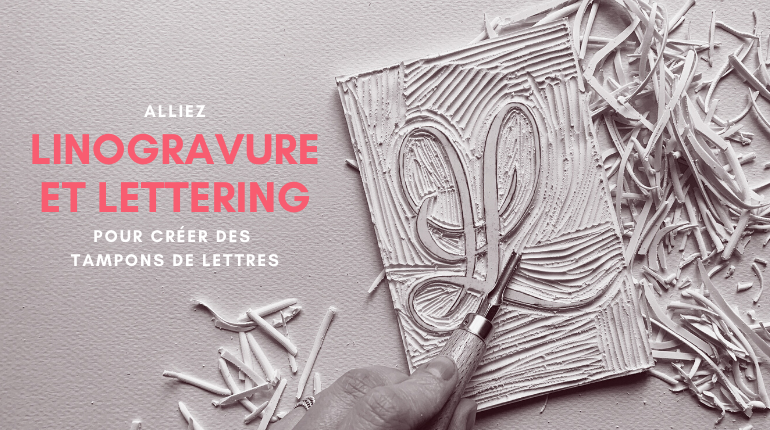
Alliez linogravure et lettering pour créer vos propres tampons de lettres
Cet article est pour tous ceux qui veulent changer de supports, d’outils et de matériaux. Fini le feutre pinceaux et la plume, place à la linogravure !
Vous connaissez ? C’est une technique de gravure qui consiste à évider certaines parties de la gomme à graver et à encrer les parties intactes (non évidées), pour imprimer le motif qu’on a ainsi créé.
C’est une super méthode pour créer des tampons de motifs et des tampons de lettres (appel à tous les fans de bullet journal !).
Pour cet exemple, j’ai allié la linogravure avec le lettering en dessinant le logo de mon studio Letter Your Life. C’est un super moyen pour dessiner des lettres et les tamponner à l’infini !
Le matériel de linogravure
Pour ce tutoriel, vous aurez besoin du matériel suivant:
- Un crayon à papier
- De la gomme à graver (ici j’ai acheté la gomme extra tendre 4mm 15x10cm de chez Essdee)
- Une gouge avec plusieurs embouts interchangeables
- Une peinture spéciale linogravure ou une peinture acrylique de la couleur que vous voulez
- Un rouleau à peindre en mousse ou un rouleau à encrer si vous avez plus de budget
Vous avez plusieurs options pour le motif :
- Partir d’un motif déjà existant en utilisant un iPad et du papier calque (ou un motif imprimé et du papier calque)
- Inventer un motif directement sur la gomme à graver
Si vous choisissez cette option, vous pouvez passer directement à l’étape 2
Etape par étape
- Appliquez une feuille de papier calque au dessus du motif que vous souhaitez faire en linogravure et tracez les contours du motif au crayon à papier.
- Retournez la feuille de papier calque à l’envers et placez la au dessus de la gomme à graver. Attention, votre motif ne doit pas dépasser la surface de la gomme.
Une fois que votre motif est bien centré, repassez sur les traits au crayon à papier pour transférer votre premier tracé sur la gomme.
- Maintenant que votre motif est tracé sur la gomme, munissez vous de la gouge et de l’embout le plus fin possible. Commencez par tracer les contours de votre motif avec la gouge puis enlevez la gomme tout autour de votre motif avec un embout plus large.
Astuces: Plus vous appuierez sur la gouge, plus elle va « creuser » profond. Pas la peine de faire tout le contour d’un coup de gouge ! Prenez votre temps et découpez petit à petit, surtout si votre motif est arrondi.
- Une fois qu’il ne reste plus que votre motif en surface, prenez votre rouleau en mousse et roulez le dans la peinture choisie.
Ensuite, faites délicatement rouler le rouleau sur votre motif. Attention de ne pas trop appuyer et de ne pas mettre de la peinture autre que sur votre motif.
- Maintenant que votre motif est enduit de peinture, vous pouvez le retourner sur le support de votre choix et bien appuyer pour transférer la peinture de la gomme au papier. Et voilà votre tampon personnalisé !
Mon avis
Je trouve que cette technique est vraiment très satisfaisante et assez simple à prendre en main. Le rendu final est aussi très différent d’une impression normale ou même d’un dessin! La gomme à graver ajoute un petit effet imparfait et vielli qui ajoute vraiment une jolie touche ! Le meilleur, c’est aussi qu’une fois le tampon réalisé, il est possible de le tamponner n’importe où et il suffit juste de nettoyer la gomme à l’eau après utilisation.